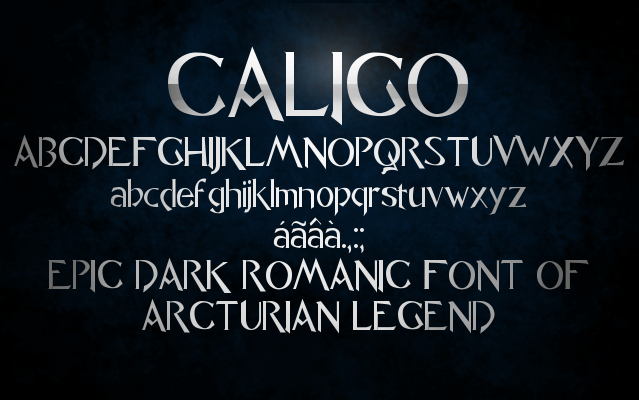
A Caligo é uma fonte inspirada nas scripts romano e italico, criada por Mateus Boga, com influências na Trajan e no Uncial. Composto pelo Typelight 3.2, essa fonte oferece uma experiência única que combina elegância e modernidade para o design de textos. Em sua essência, a Caligo transmite um ar rico em história e cultura graças às suas origens clássicas. Seja você um designer gráfico ou um criador de materiais digitais, este é um recurso fonte que trará originalidade aos seus projetos, valorizando seu trabalho com uma combinação única de design e estilo. Na categoria de Fonts Não-Latinas, a Caligo se destaca pela sua singularidade. Inspirada nos scripts clássicos dos anos romanos, ela oferece um conjunto de caracteres que pode ser facilmente integrado em qualquer projeto cultural ou histórico para qual o seu designer preferido busca uma fonte ideal. Com sua estrutura sólida e leitura confortável, a Caligo é perfeita tanto para uso em design gráfico como em impressão digital. Não hesite em experimentar essa fonte única que pode revolucionar a maneira como você visualiza o seu trabalho de design.